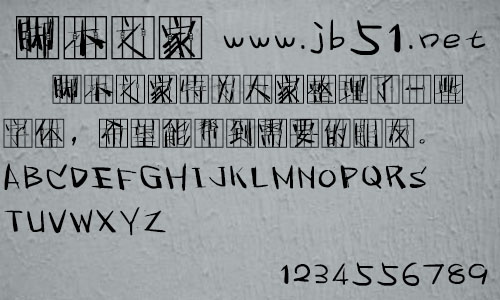
方正duang体简
方正duang体由方正字库出品的一款不错的艺术字体,笔画刚硬狂野,与浮动的方框、铁窗形成鲜明的对比,适合应用于艺术设计、平面宣传设计、网页设计,书法等领域。
方正duang体 由漫画家于彦舒在方正呐喊体的基础上做的二次创作,试图表达一种呐喊、自嘲、发泄、冲破束缚的情感,来排解年轻人在网络生活中的负面情绪。这款字体的笔画刚硬狂野,与浮动的方框、铁窗形成鲜明的对比,如一个人强烈试图挣脱某种困境。